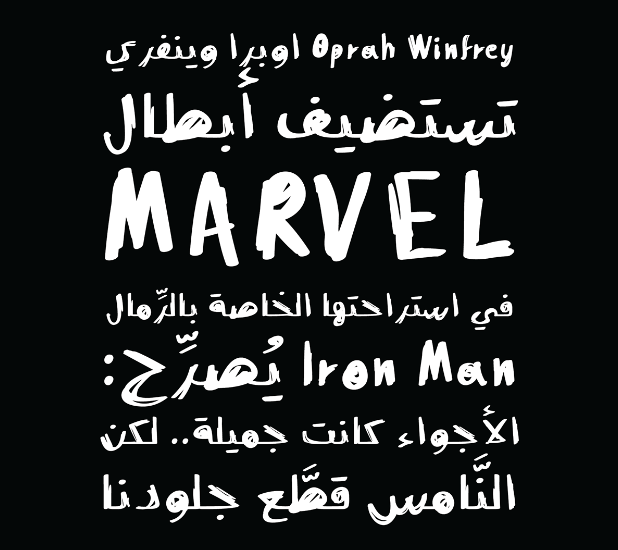
فونت وهم
نسخه رایگان فونت عربی وهم Wahm Two Typeface که فاقد حروف کچ پژ می باشد (برای تهیه نسخه غیر رایگان باید به سایت مرجع فونت مراجعه فرمایید) به علت اضافه کردن چند مجموعه کاراکتر غیر لاتین فونت جهانی محسوب میشود این فونت برای کار هویت سازمانی، طراحی سرمقاله و پروژه های UI / UX بهینه شده است این فونت عربی ساخته طراح عرب Fahd Al Fraikh در دسته بندی طراحان عرب سایت ایران فونت قرار گرفته شد